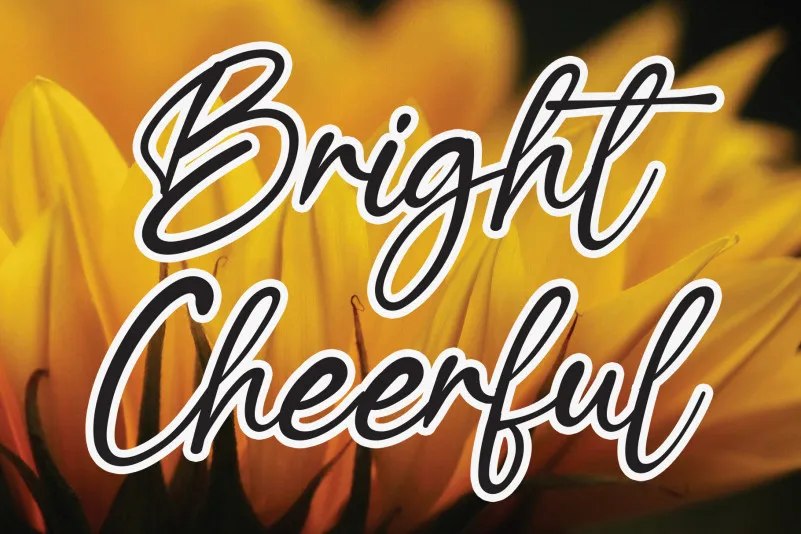
A fonte ‘Bright Cheerful Script Font’ é uma escolha perfeita para criar designs vivaz e trendy. Inspirada por uma suave corrente de escrita manual, ela traz um toque divertido e atual aos seus projetos digitais. A fonte é apropriada para diversos usos gráficos como branding, embalagens de produtos, convites, frases curtas, camisetas personalizadas, rótulos, outdoors e logotipos. É ideal para qualquer situação que você possa imaginar decorar com um ar descontraído e encantador. Que tal experimentar uma fonte tão alegre? Será ótimo adicionar um toque especial a seus projetos!